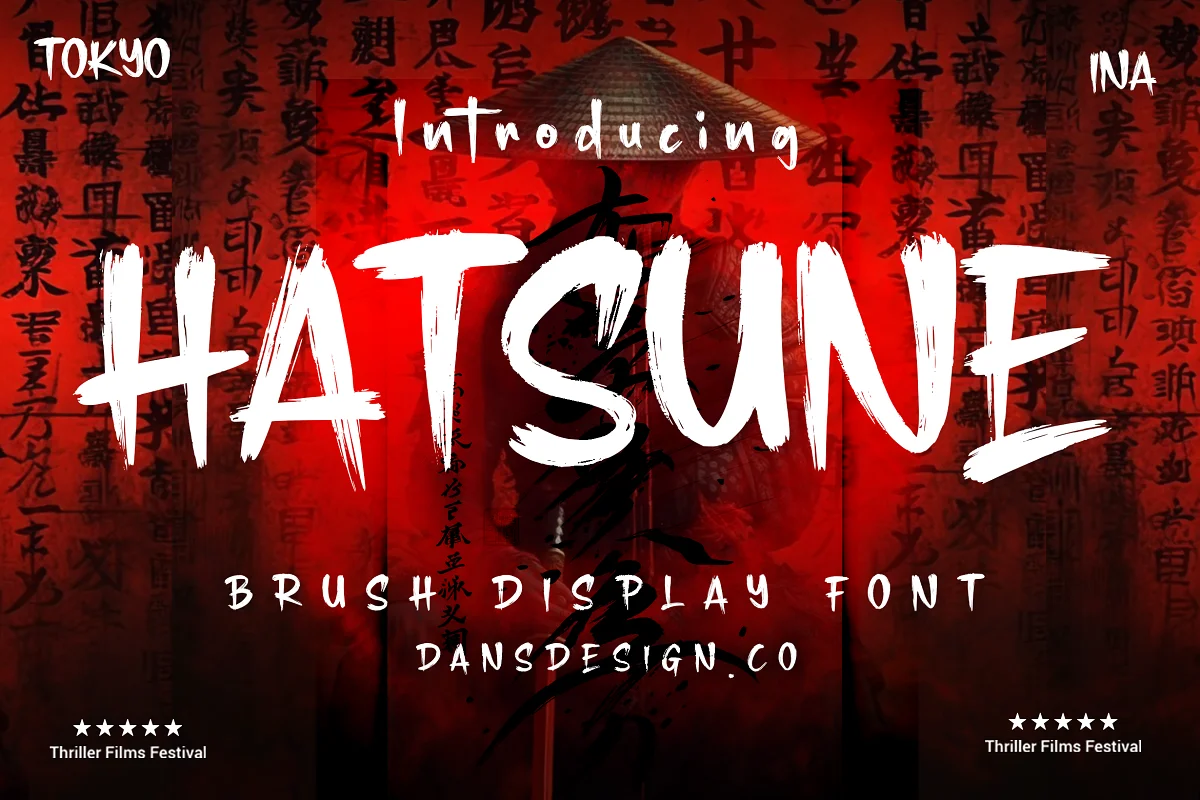
دانلود فونت Hatsune Brush Display Font
Dansdesign با افتخار Funt Display Hatsune Brush را ارائه می دهد، این فونت با ارجاع به حروف مختلفی ساخته شده است که من با سبک خود ترکیب و طراحی می کنم.
قلم صفحه نمایش براش Hatsune متمایز و با جزئیات بسیار زیاد. این یک انتخاب عالی برای طرح های نفیس یکپارچه سازی شهری، نام تجاری تجاری خالکوبی، لوگوها، طرح های قدیمی و غیره خواهد بود.